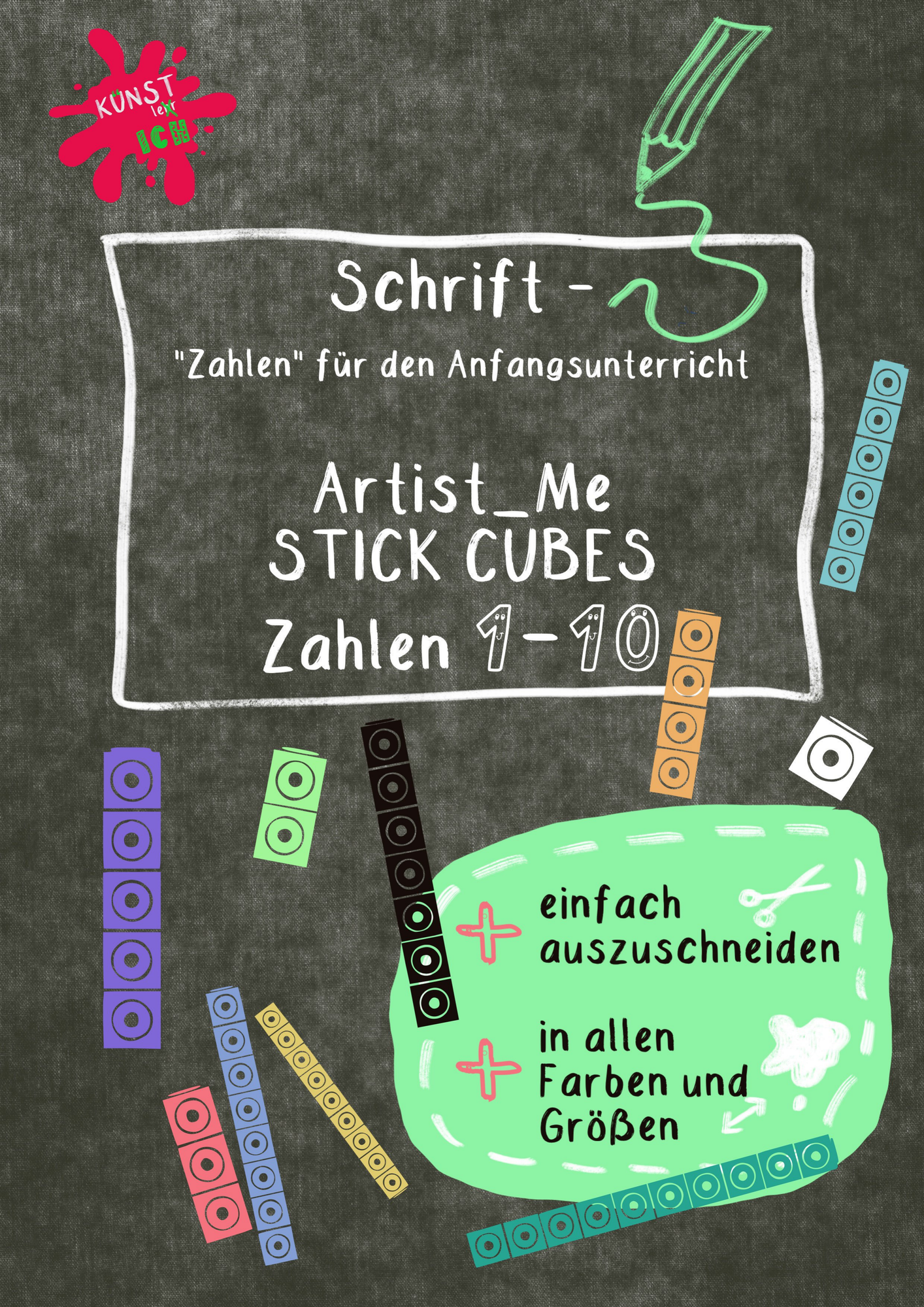
selbst erstellte Cliparts/Grafiken - Schrift / Ziffern / Font für den Anfangsunterricht - Steckwürfel - 2 Varianten - Artist Me - Stick Cubes - ART.ist_ME // Kuenstler_Ich - Deckblatt
Diese „Schriften“ erleichtern die Gestaltung von Arbeitsblättern im Zahlenraum bis 10, 20 und 100.
Die einen Steckwürfel sind bis auf das Loch in der Mitte ausgefüllt und können daher auch von SchülerInnen sehr gut ausgeschnitten werden. Die anderen zeigen lediglich die Konturen.
Da es keine 10 auf der Tastatur gibt, habe ich sie  dem Fragezeichen zugeordnet.
Schaue dir die beiden Beispielseiten an. Hier sieht man die Schriften in schwarz und weiß.
Schrift / Ziffern / Font für den Anfangsunterricht - Steckwürfel - 2 Varianten - Artist Me - Stick Cubes
Schrift / Ziffern / Font für den Anfangsunterricht - Steckwürfel - Artist Me - Stick Cubes
Diese Schrift erleichtert die Gestaltung von Arbeitsblättern im Zahlenraum bis 10, 20 und 100.Diese Steckwürfel sind bis auf das Loch in der Mitte ausgefüllt und können daher auch von SchülerInnen sehr gut ausgeschnitten werden.Da es keine 10 auf der Tastatur gibt, habe ich sie  dem Fragezeichen zugeordnet. Die Schrift ist in den Formaten ttf und otf angehängt.Schaue dir die beiden Beispielseiten an. Hier sieht man die Schrift in schwarz und weiß.Ich wünsche viel Spaß beim Einsatz ;)Kuenstler_Ich
Schrift / Ziffern / Font für den Anfangsunterricht - Steckwürfel - Artist Me - Stick Cubes Hollow
Diese Schrift erleichtert die Gestaltung von Arbeitsblättern im Zahlenraum bis 10, 20 und 100.Diese Steckwürfel sind lediglich in ihren Konturen deckend!Da es keine 10 auf der Tastatur gibt, habe ich sie  dem Fragezeichen zugeordnet. Die Schrift ist in den Formaten ttf und otf angehängt.Schaue dir die beiden Beispielseiten an. Hier sieht man die Schrift in schwarz und weiß.Ich wünsche viel Spaß beim Einsatz ;)Kuenstler_Ich